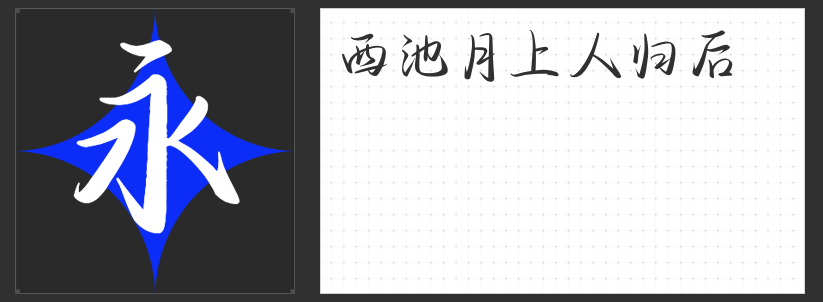
端午墨韵,字载乾坤——四款匠心字体赋能节日设计
端午临仲夏,粽香伴墨香。当传统佳节邂逅匠心字体,文化底蕴与视觉张力便在笔锋流转间交融共生。以下四款非免费但风格独特的字体,以多元笔触诠释端午精神,为商业海报、包装、短视频等设计注入鲜活生命力。
一、励字造仲夏简 常规
这款字体以“仲夏”为名,恰似端午时节荷叶初展的清新。笔画坚挺如龙舟桨影,边缘斑驳似竹简残卷,钩笔洒脱如江风拂苇。其字形端正却不失灵动,通用性极强——商业海报中,它可勾勒节日的现代活力;包装设计里,又能以手写温度传递传统匠心。一笔一划间,既有端午的烟火气,亦藏文人的风骨情。
二、造字侠伏魔简繁 传神
以“伏魔”为名,这款字体自带磅礴气场。笔墨浓淡如墨汁入水,粗细对比似江涛拍岸,夸张的勾提挑捺如龙舟竞渡的呐喊,单字结构收放间尽显张力。在端午主题海报中,它可化身“驱五毒”的符咒,以凌厉笔锋震慑邪祟;在短视频标题里,又能以强烈的视觉冲击力抢占观众目光,让传统习俗焕发先锋气质。
三、造字侠仗剑简繁 传神
若说“伏魔”是降妖除魔的利刃,那么“仗剑”便是仗剑天涯的侠客。这款字体折提如刀光剑影,钩画似浪遏飞舟,高度折叠的笔画间尽显江湖快意。在端午龙舟赛的宣传中,它能以刚劲笔触点燃热血;在国风文创包装上,又能以潇洒字形诠释“侠之大者,为国为民”的端午精神,让传统与武侠情怀碰撞出别样火花。
四、字圈也字风满袖行楷
这款行楷以“风满袖”为韵,在楷书骨架中融入行书游丝。连笔如粽叶缠丝,左勾竖出锋似龙舟破浪,既有正书的严谨法度,又得草书的飘逸神采。在端午书籍封面或新媒体海报中,它可化作屈子行吟的诗句,以荡气回肠的笔意传递家国情怀;在高端礼盒设计里,又能以行云流水的姿态诠释“上善若水”的东方哲学。
四款字体,或如清风拂柳,或似惊雷破空,或携侠骨柔情,或蕴诗心墨韵。它们不仅是文字的载体,更是端午文化的视觉转译者。设计师可依场景择其精髓,让笔墨与节日共鸣,让设计在传统与现代的经纬中,织就一幅幅独具韵味的端午画卷。